Как оформить указатели в торговом центре без визуального хаоса
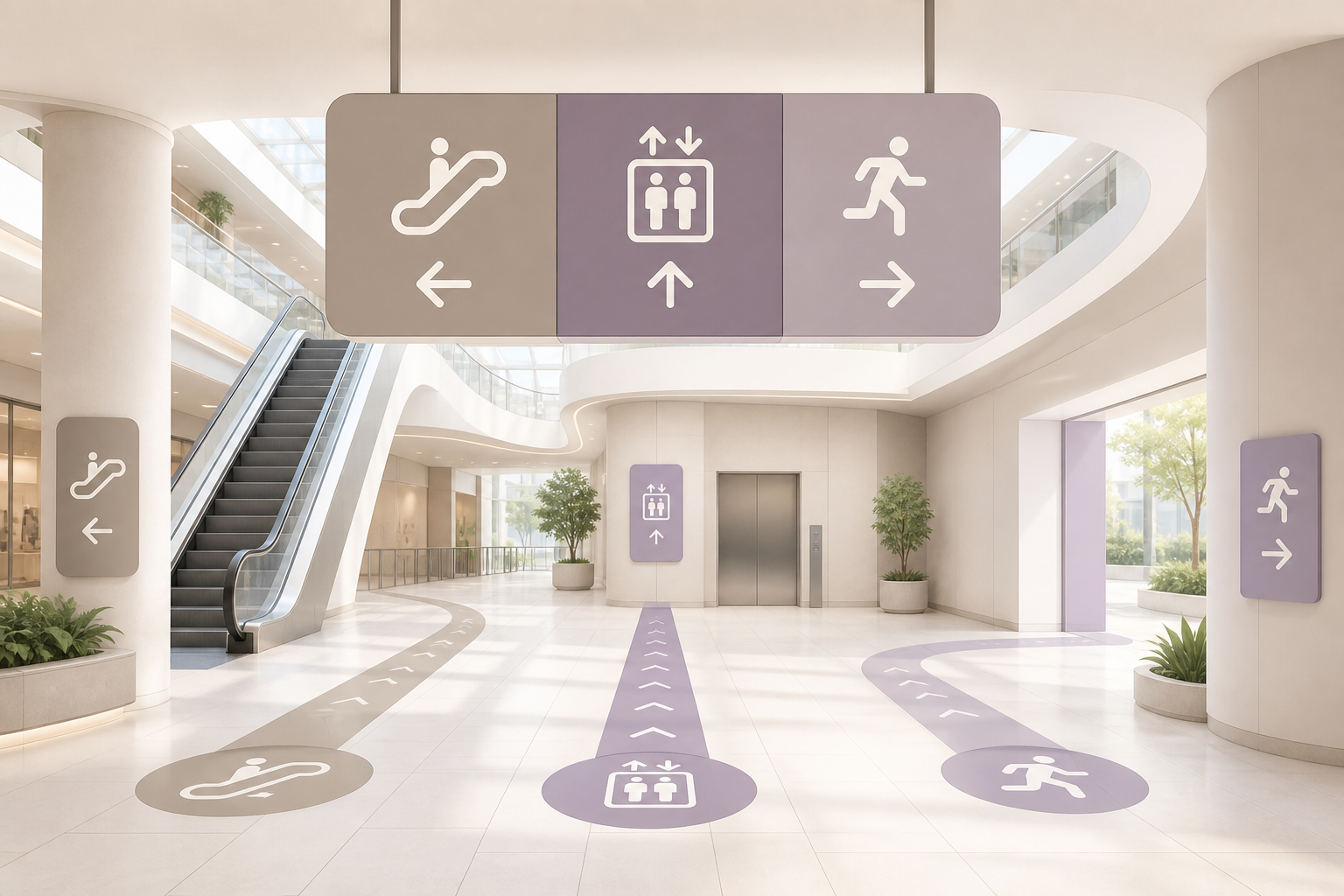
Чтобы оформить указатели в торговом центре без визуального хаоса, нужно сначала создать единую навигационную систему: определить маршруты, уровни информации, правила шрифта, цвета, пиктограмм и размещения. Отдельные красивые таблички не решают задачу, если они противоречат друг другу или появляются слишком поздно. Ниже — практический алгоритм проектирования понятной навигации.
Почему навигация в ТЦ превращается в визуальный хаос
В торговом центре одновременно работают архитектура, коммерческие вывески, рекламные носители, брендинг арендаторов и навигационные элементы. Каждый объект пытается привлечь внимание, но посетителю нужен не максимальный объём информации, а быстрый ответ на конкретный вопрос: где нужный магазин, как попасть на другой этаж, где находятся туалеты, лифт, эскалатор, парковка или выход. Хаос возникает, когда все сообщения оформлены одинаково громко.
Обычно проблема начинается не со шрифта, а с отсутствия правил. Указатели добавляют по мере открытия новых магазинов, меняют после ремонта или заказывают у разных подрядчиков. В результате на одном этаже появляются разные стрелки, оттенки, размеры букв и способы написания названий. Посетитель вынужден каждый раз заново расшифровывать систему вместо того, чтобы следовать ей автоматически.
Сначала определите навигационную задачу и маршруты
До выбора шрифта и материала составьте карту основных сценариев. Отметьте точки входа, парковку, лестницы, лифты, эскалаторы, фуд-корт, кинотеатр, санузлы, детские зоны, магазины-магниты и аварийные выходы. Навигация должна помогать пройти путь от точки принятия решения до цели, а не просто перечислять все объекты, которые находятся в здании.
Разделите информацию по уровням важности
Понятная система обычно строится в несколько уровней. Первый уровень сообщает направление: «Магазины», «Парковка», «Выход». Второй уточняет зону или этаж: «1 этаж», «Сектор B», «Галерея ресторанов». Третий содержит конкретную цель: название магазина, номер парковочного ряда или обозначение сервиса. Не смешивайте эти уровни в одну строку, иначе посетителю будет трудно понять, что читать первым.
Покажите решения в точках выбора
Указатель нужен прежде всего там, где человек должен принять решение: повернуть, выбрать эскалатор, перейти в другой корпус или свернуть в коридор. Если поставить табличку только возле цели, она не поможет посетителю, который уже выбрал неправильный маршрут. Проверьте путь глазами нового гостя и добавьте подтверждающие указатели после каждого важного поворота.
Выстройте единую типографическую систему
Шрифт для указателей в торговом центре должен быть прежде всего читаемым на расстоянии и в движении. Декоративность, необычные соединения букв и чрезмерно тонкие начертания мешают распознаванию. Для основной навигации обычно выбирают нейтральный гротеск или другой шрифт с ясными формами, хорошим различием похожих знаков и устойчивой кириллицей.
Проверьте, как гарнитура выглядит в реальных словах: «эскалатор», «санузел», «парковка», «выход», названиях магазинов и обозначениях этажей. Важно оценивать не только отдельные буквы, но и плотность строки, межбуквенное расстояние, длину слов и работу в верхнем и нижнем регистре. Если навигация двуязычная, протестируйте кириллицу и латиницу рядом, а не по отдельности.
Ограничьте количество начертаний и регистров
Для одной системы достаточно определить роли: основное направление, уточнение, служебная информация и, при необходимости, предупреждение. Каждой роли можно назначить начертание, размер или цвет. Не используйте одновременно капслок, курсив, жирный шрифт, обводку и тень для привлечения внимания. Иерархия должна считываться по правилам, а не по количеству эффектов.
Настройте контраст и расстояние между элементами
Читаемость зависит от контраста текста и фона, размера букв, межстрочного интервала и свободного пространства вокруг надписи. Плотно заполненная табличка выглядит информативной только на макете, но теряет ясность в реальном проходе. Оставляйте заметные поля, отделяйте стрелку от текста и не прижимайте пиктограммы к краям носителя.
Используйте цвет и пиктограммы как систему, а не декор
Цвет помогает быстро различать зоны, этажи или типы объектов, но не должен быть единственным способом передачи смысла. Один оттенок можно закрепить за парковкой, другой — за общественными сервисами, третий — за торговыми галереями. При этом текст и пиктограмма должны оставаться понятными без цвета: это важно при плохом освещении, печати и для людей с особенностями восприятия.
Пиктограммы особенно полезны для туалетов, лифтов, эскалаторов, выхода, камеры хранения и парковки. Выберите один визуальный стиль: одинаковую толщину линий, степень детализации, форму рамок и принцип размещения. Не смешивайте реалистичные иллюстрации с простыми символами. Стрелка также должна быть унифицирована: одинаковое направление, пропорции и визуальный вес на всех носителях.
Вывод: навигация должна быть последовательной
Хорошие указатели в торговом центре не конкурируют с посетителем за внимание. Они заранее подсказывают направление, используют единый шрифт и графику, поддерживают маршрут в точках выбора и остаются понятными без лишних эффектов. Начинайте с карты сценариев и правил системы, а затем проверяйте дизайн в реальном пространстве.